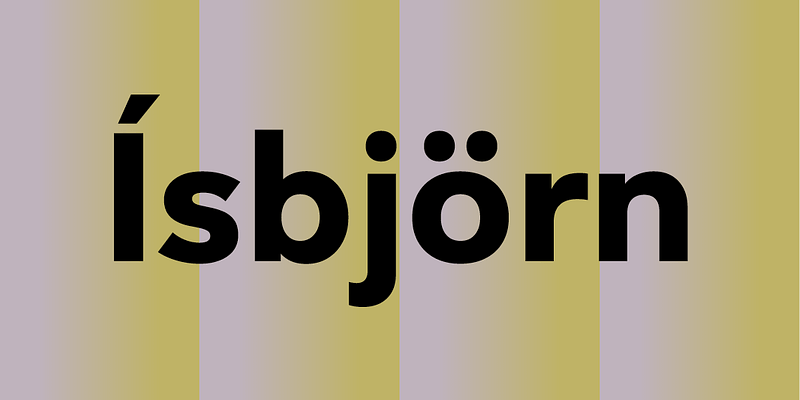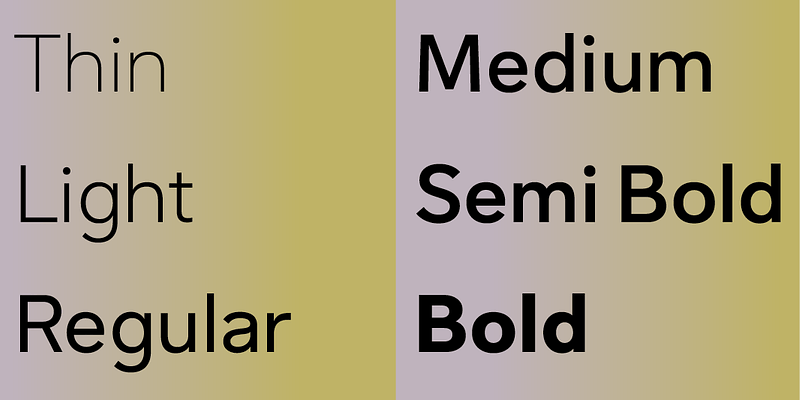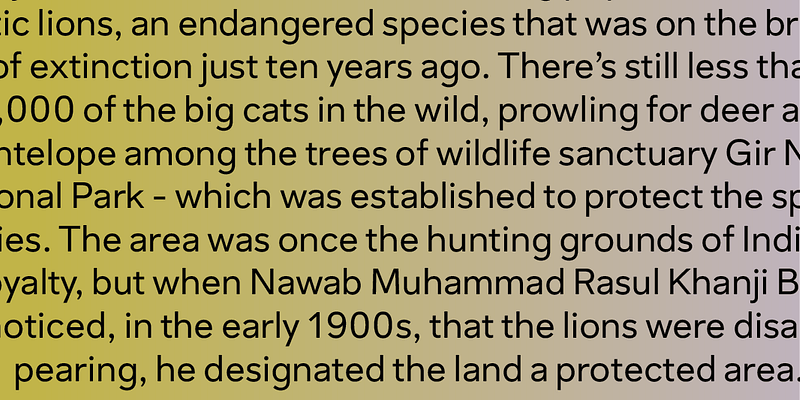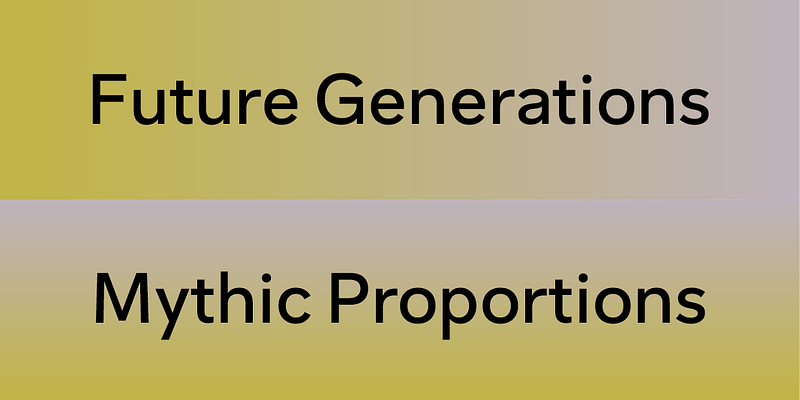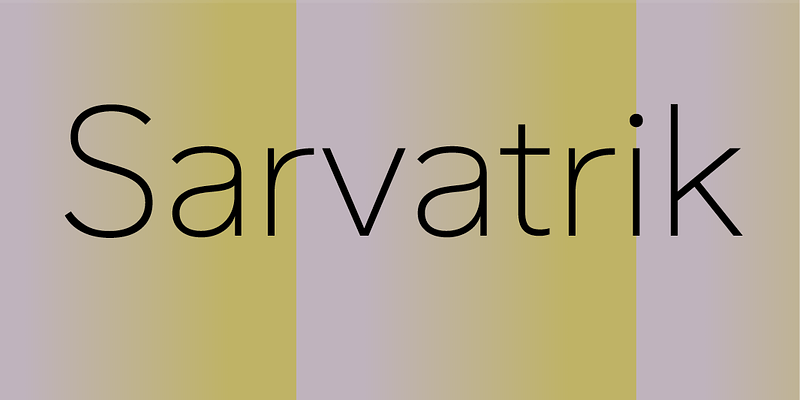
Sarvatrik は、Bangla 語、Devanagari 語、Gurmukhi 語、ラテン語にわたる言語サポートに加え、堅牢なウェイトセットを提供します。さらに多くのインド文字が続く予定です。実用的な選択肢であり、大小両方のサイズで優れたパフォーマンスを発揮しますが、フレンドリーでオープンな性格を損なうことはありません。ラテン語バージョンはバングラ語、Devanagari 語、Gurmukhi 語とシームレスに連携するため、多言語のブランディングや複数の市場で活動する企業に適しています。
書記体系 : ラテン語、Devanagari 語、Bangla 語、Gurmukhi 語
Universal Thirst は、インド文字とラテン文字を専門とする活字フォントメーカーです。2016 年にデザイナー兼エンジニアの、Gunnar Vilhjálmsson と Kalapi Gajjar の二人組によって設立されました。彼らは、対照的な視覚的伝統を活用して、活字に対するユニークで二重の視点を提供します。